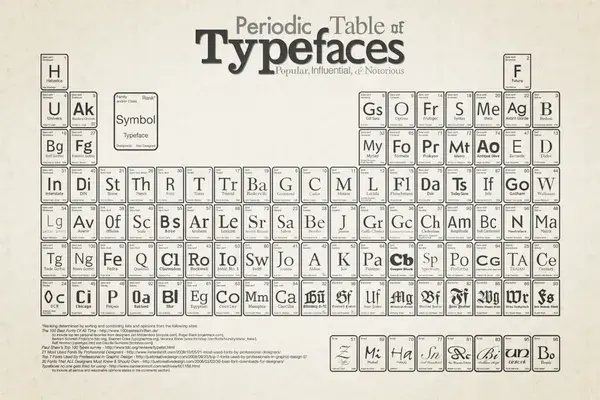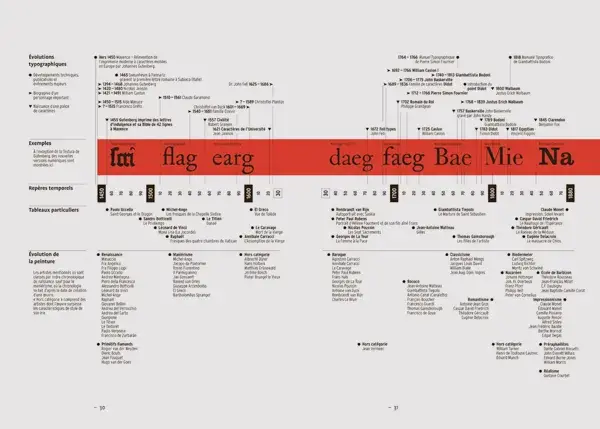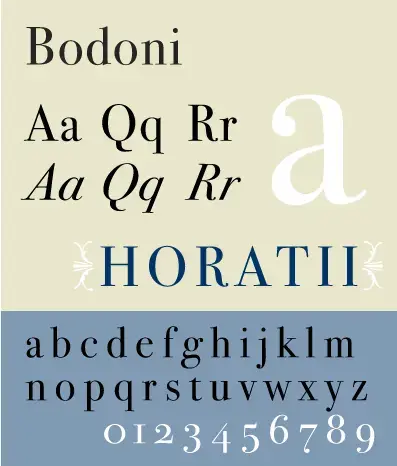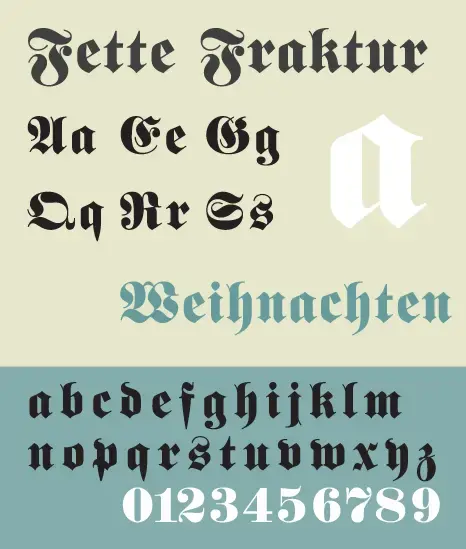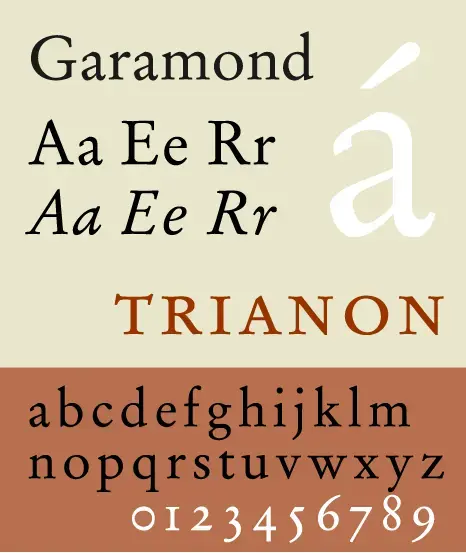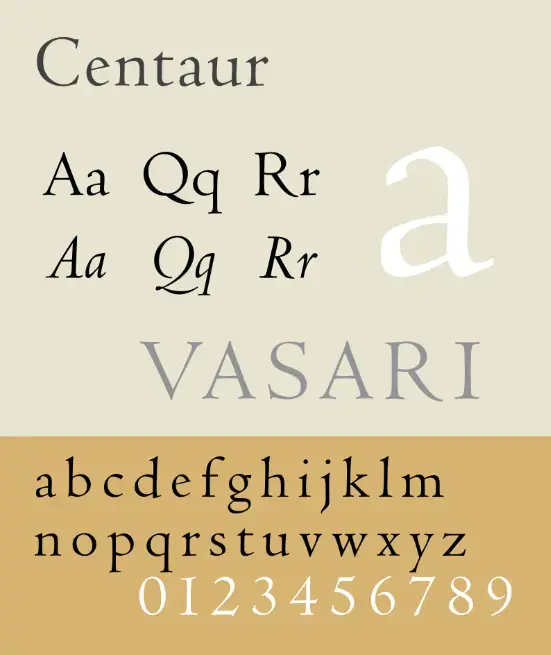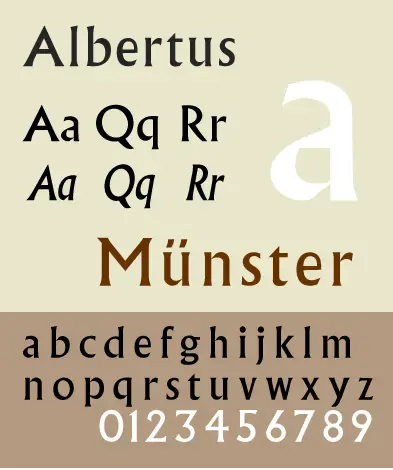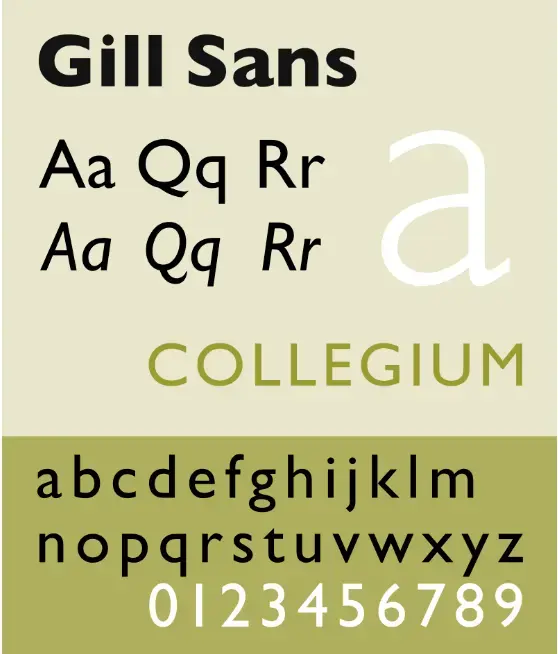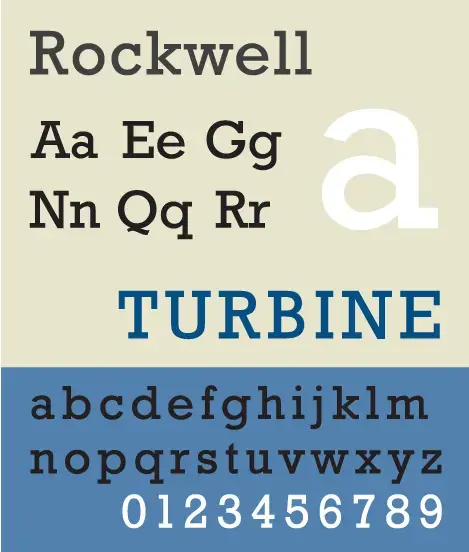
Histoire et Familles de typographie
Voici le deuxième volume de notre dossier sur "La Typographie", après avoir vu "La structure et le vocabulaire de la lettre" dans le premier numéro, aujourd'hui nous allons nous intéresser à son histoire et son évolution.
Histoire de la typographie
Le terme "typographie" est arrivé avec la naissance de l’imprimerie vers 1440, avec la technique d’impression. On disposait des caractères mobiles (en plomb) pour former des mots et des phrases. Depuis ce temps les techniques et l’utilisation des typographies n’ont cessées d’évoluer en devenant automatiques à l’aide de la Linotype vers 1880 (composition sur un clavier puis fonte de la ligne-bloc) pour ensuite arriver à nos jours avec l’ère du numérique.
Celui-ci à fait connaitre un essor à la typographie, la création et l’utilisation de celle-ci se fait beaucoup plus facilement. Elle crée des liens visuels et logiques dans le but de rendre attractive une lecture, on l’utilise comme ornement ou pour renforcer une identité graphique (logo, publicité).
La typographie nous aide en tant que graphiste à connoter et donner des valeurs à nos projets quels qu’ils soient, elle fait partie intégrante de notre métier. Mais pour ça il faut en connaître les codes et les langages. Intéressons-nous aux familles de typographies avec les origines des caractères…
Familles et Classifications Typographiques
Afin de mieux appréhender la richesse offerte par les différents caractères, des typographes ont tenté de regrouper les caractères présentant des caractéristiques graphiques similaires en familles. Ces classifications sont arbitraires et sont basées sur la norme DIN 16 518.
Les Humanes (Vénitiennes Old Style)
Utilisées par les imprimeurs vénitiens du XV siècle, ce sont les premiers caractères non gothiques employés en imprimerie. On les distingue par les empattements en forme triangulaire, courts et épais, les pleins et déliés des lettres rondes sont symétriques par rapport à l’axe oblique. (Centaur, Guardi, Barkeley)
Les Garaldes
Représentent les lettres typiques de la Haute-Renaissances du XVI et XVII siècle, le terme "Garalde" vient des célèbres imprimeurs et graveurs Claude Garamond et Alde Manuce. Ses caractéristiques sont semblables à la classe des "Humanes" mais ses proportions sont plus élégantes, la traverse du "e" est horizontale.
Les Réales
Inspirées du style baroque, le tracé des caractères est plus construit avec une prédominance des courbes. Les empattements sont incisés et triangulaires, les pleins sont épais tandis que les déliés sont maigres. (Baskerville, Times roman)
Les Didones
Introduit durant l’époque du néo-classique (XVIII siècle), le mot Didone vient des noms des créateurs Didot et Bodoni. On les reconnait par les déliés et les empattements qui sont rectilignes et de même épaisseur, de plus les pleins et déliés des lettres rondes sont symétriques par rapport à l’axe vertical.
Les Mécanes (Égyptienne)
Le nom "Mécane" signifie mécanique/mécanisation, qui connote la forme très géométrique des caractères, leurs empattements sont bien marqués et rectangulaires et l’épaisseur du trait est constant. (Rockwell, Glypha, Figaro)
Les Linéales
La lettre est composée de lignes et seulement de lignes, comme son nom l’indique. Car on ne trouve pas d’empattements (Sans Serif), sa composition reste nette et lisible et permet d’être très fonctionnelle. (Helvética, Futura, Gill Sans).
Les Incises
Les Incises imitent les caractères taillés dans la pierre semblable à l’époque romaine (antique), elle est caractérisée par son dessin en bâton dont les terminales s’élargissent. (Albertus, Castellar)
Les Scriptes
Ce sont toutes les typographies qui imitent l’écriture à main levée, elles possèdent une grande diversité. C’est l’outil utilisé qui détermine sa forme (crayon, plume, feutre, ..etc). (Palace, Anglaise, Bison)
Les Manuaires (Manuscrites)
Tout comme les "Scripts" les lettres imitent l’écriture manuelle, mais elles évoquent l’époque avant l’apparition de la typographie (1440) , comme le Moyen Âge. Une autre différence vient des lettres qui ne sont pas liées entre-elles. (Carolina, Codex)
Les Fractures (Gothique)
Ou plus communément appelées "Gothique", ce type de lettres imite l’écriture à la plume large et s’inspire de l’architecture ogivale. C’est l’un des premiers caractères typographiques utilisé par Gutenberg. (Fraktur, Rotunda, Textura)
Autres termes utilisés
Serif : des fonts à empattement.
Sans Serif : des fonts sans empattement.
Cursive : des fonts simulant l’écriture à la main.
Pour la suite…
Ces 2 premiers volumes sur la typographie étaient en grande partie portés sur son côté technique qui peut être un peu barbant pour certains, mais qui reste essentiels pour une bonne compréhension de celle-ci. Si vous souhaitez créer ou travailler sur de la typographie cela vous sera utile, autant pour vos présentations que pour votre culture. Les prochains numéros seront d’avantage ciblés sur le côté créatif de la typographie de nos jours et son utilisation dans le graphisme.